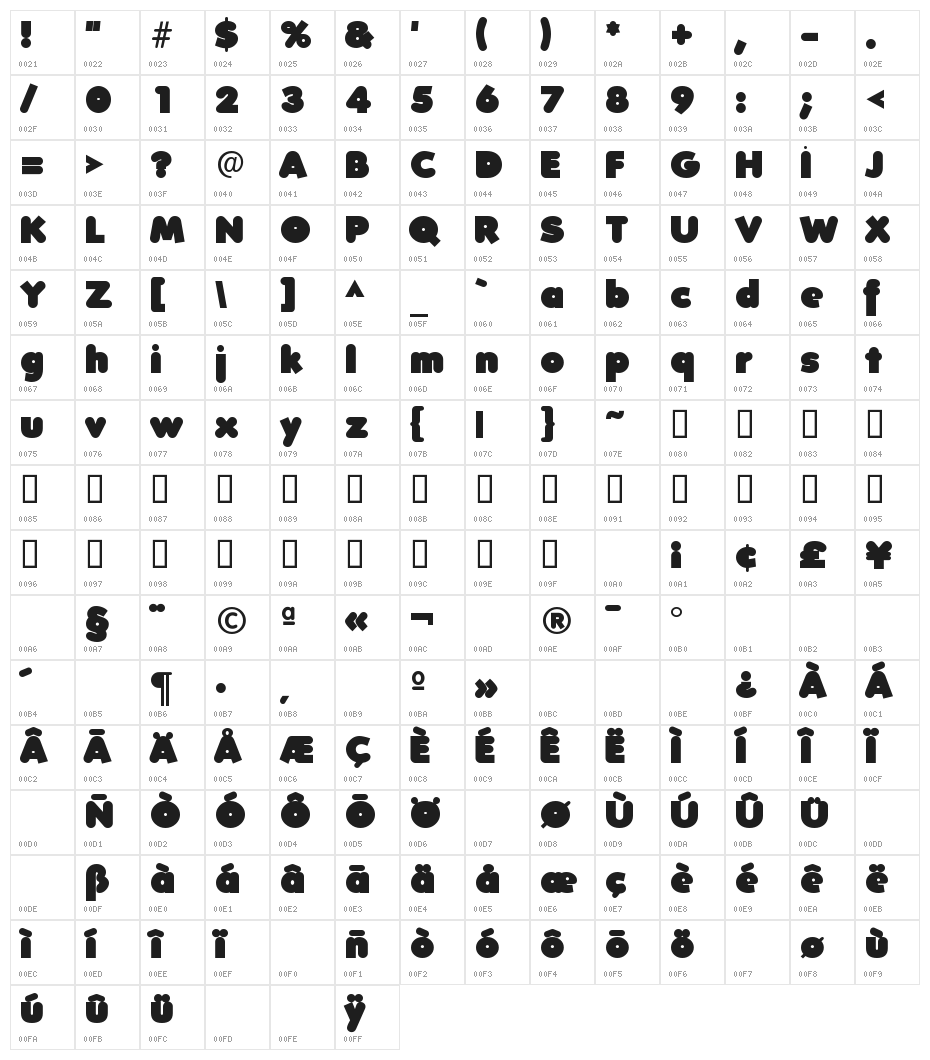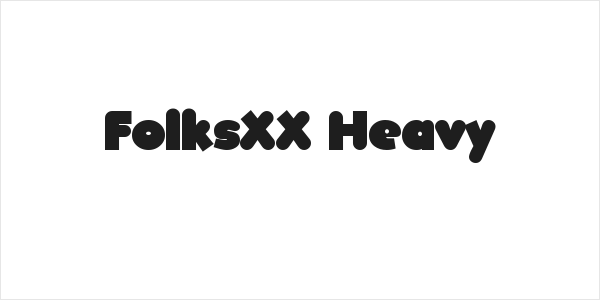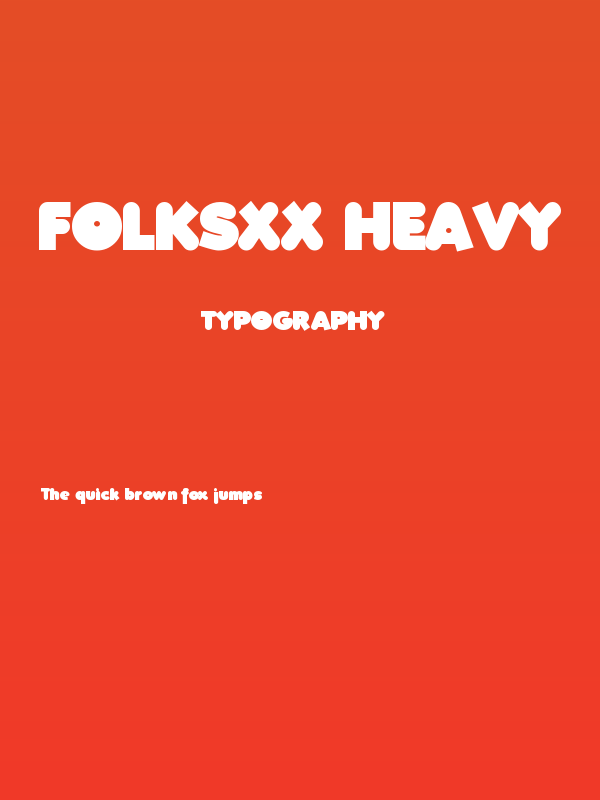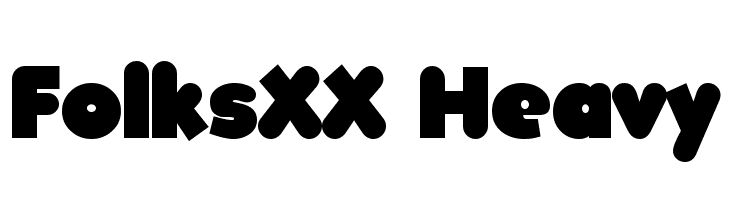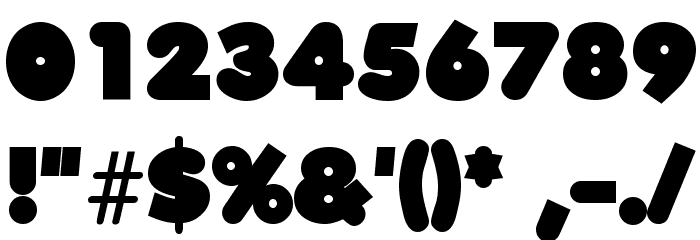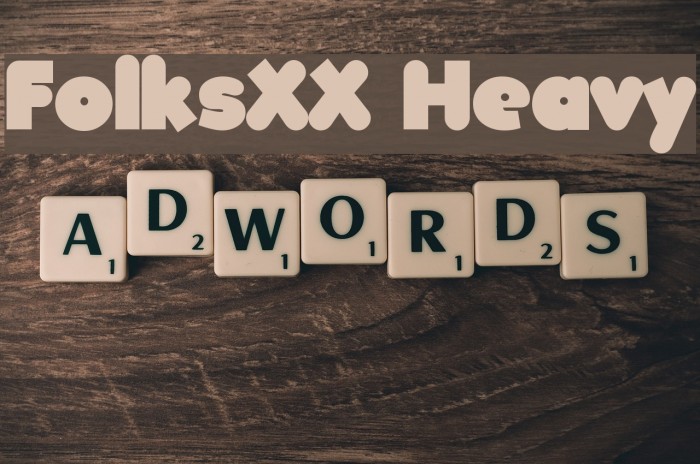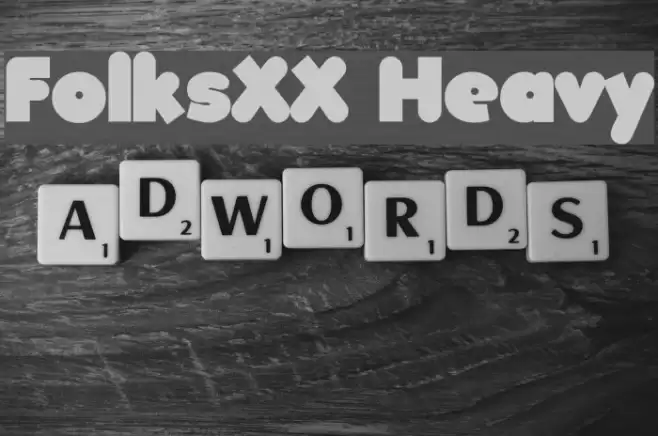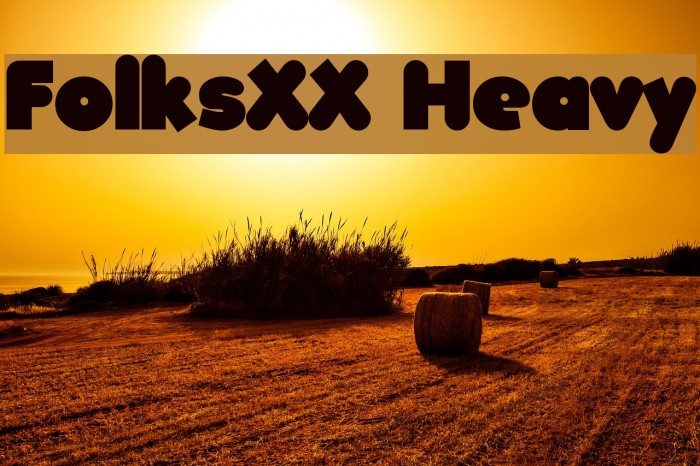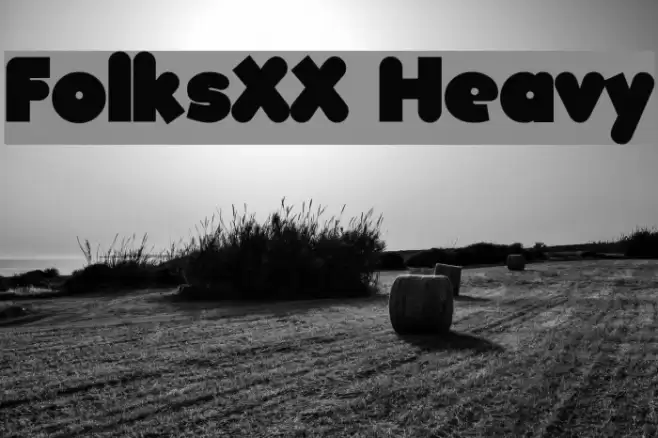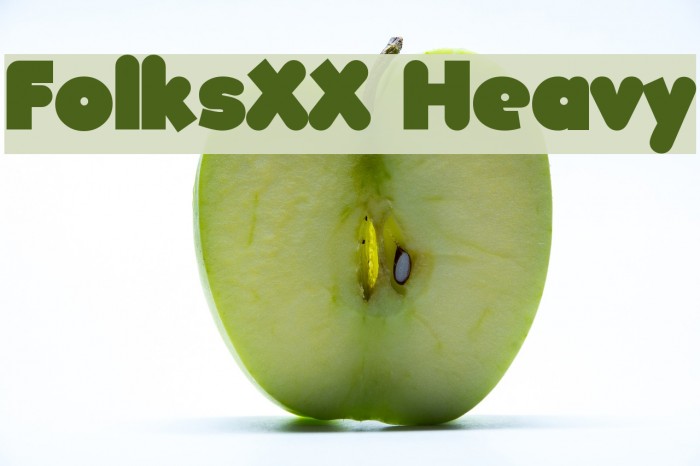
FolksXX Heavy Font
| Estilo general | Playful, Modern |
| Proyectos propuestos | Ideal for children's books, playful branding, posters, and any project requiring a fun, approachable aesthetic. |